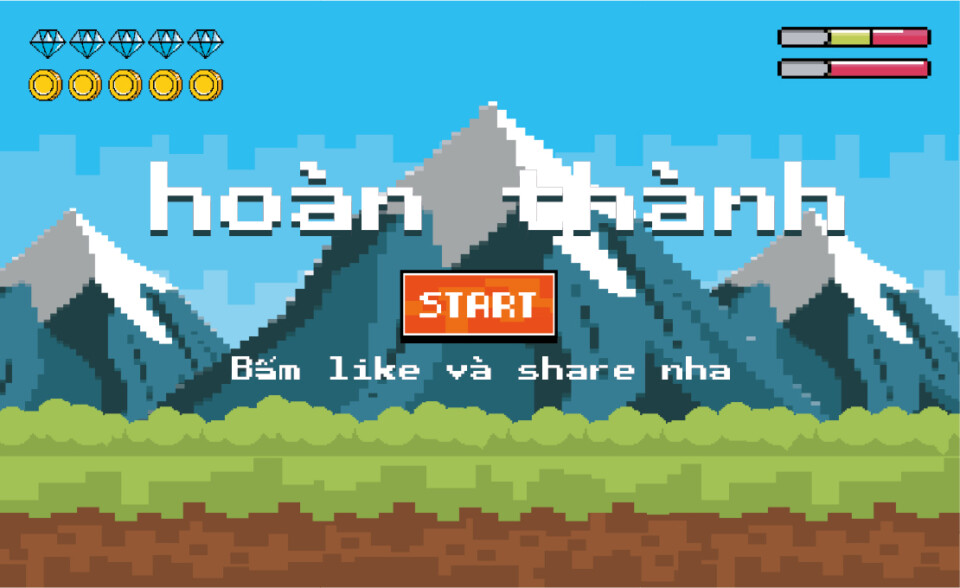
Trong hệ thống giáo dục Việt Nam, việc sử dụng các Font Chữ chuẩn mẫu của Bộ Giáo dục luôn là ưu tiên hàng đầu. Font tiếng Việt KVN-97 là một trong những bộ phông chữ đặc thù, được thiết kế tỉ mỉ để phục vụ nhu cầu soạn thảo văn bản, in ấn tài liệu giảng dạy và trình bày đồ án học đường. Với sự chính xác về các dấu thanh và ký tự đặc trưng, bộ font này giúp người dùng tránh được lỗi hiển thị phổ biến khi làm việc trên các nền tảng máy tính hiện đại.
Đặc điểm nổi bật của Font tiếng Việt KVN-97
Bộ font này sở hữu những ưu điểm vượt trội về độ nét và tính ứng dụng cao trong môi trường sư phạm. Các nét chữ được tinh chỉnh để giữ nguyên bản sắc văn hóa Việt Nam nhưng vẫn đảm bảo tính thẩm mỹ hiện đại.
Khả năng tương thích và định dạng
Font tiếng Việt KVN-97 được mã hóa theo các bảng mã phổ biến, giúp người dùng dễ dàng cài đặt trên hệ điều hành Windows hoặc macOS. Độ dày nét chữ vừa phải giúp việc đọc văn bản trong thời gian dài không gây mỏi mắt, phù hợp cho cả học sinh và giáo viên khi soạn bài giảng điện tử hoặc làm bài tập nhóm.
Tính ứng dụng trong thiết kế đồ họa
Không chỉ dừng lại ở soạn thảo, bộ phông này còn được giới thiết kế tin dùng cho các ấn phẩm như poster cổ động, bìa sách giáo khoa hay các bảng hiệu trường học. Sự trang trọng và rõ ràng của nó tạo nên phong cách chuyên nghiệp, giúp thông điệp truyền tải một cách trực quan nhất.